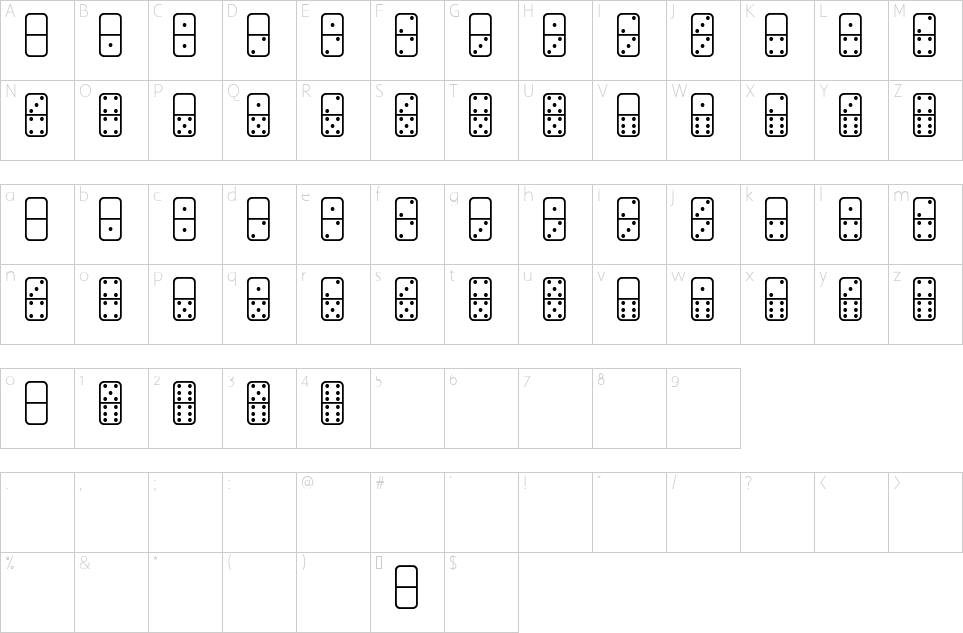
Aqui está uma descrição envolvente e natural para a página de download da font ‘Dominos Font’, seguindo as instruções fornecidas: Descubra o charme inconfundível da ‘Dominos Font’ com este recurso gratuito, especialmente projetado para quem busca um toque moderno em suas criações digitais. Desenvolvida por Southype, esta font é perfeita tanto para usuários de Windows quanto Mac, e já foi baixada 4.411 vezes, um número que ilustra a popularidade crescente dela. Com linhas elegantes e uma tipografia cuidadosamente concebida, ‘Dominos Font’ traz um toque contemporâneo à sua produção visual. É perfeito para dar um toque único em qualquer projeto digital, seja para o seu blog pessoal, o site da sua empresa ou até mesmo como um elemento de estilo personalizado na sua nova identidade corporativa. Baixe a ‘Dominos Font’ agora e desfrute do aspecto moderno que essa font tem a oferecer. Essa não é apenas uma maneira de adicionar beleza à sua criação, mas também uma maneira de mostrar sua individualidade no meio digital.